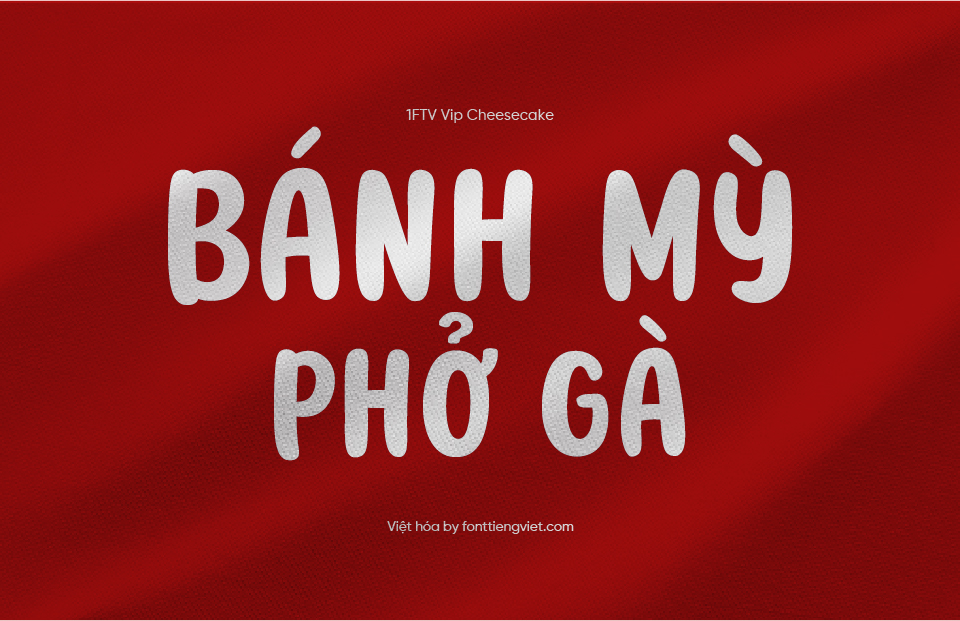
Font Việt hóa 1FTV Vip Cheesecake
Giới thiệu về Font Việt hóa 1FTV Vip Cheesecake
Trong thế giới thiết kế đồ họa hiện nay, việc tìm kiếm một mẫu Font Miễn Phí độc đáo và ấn tượng luôn là ưu tiên hàng đầu của các bạn học sinh và thầy cô giáo. Font Việt hóa 1FTV Vip Cheesecake nổi bật như một lựa chọn hoàn hảo cho các dự án sáng tạo nhờ phong cách ngọt ngào, mềm mại giống như tên gọi của một món tráng miệng hấp dẫn. Đây là bộ phông chữ được tinh chỉnh kỹ lưỡng về dấu tiếng Việt, giúp người dùng dễ dàng trình bày nội dung mà không lo lỗi hiển thị hay mất thẩm mỹ.
Đặc điểm nổi bật của bộ font chữ này
Phong cách thiết kế sáng tạo
Font Việt hóa 1FTV Vip Cheesecake mang trong mình nét vẽ phóng khoáng nhưng không kém phần chỉn chu. Các đường cong của chữ được bo tròn tạo cảm giác thân thiện, gần gũi và đầy năng lượng. Điều này giúp bộ font trở nên cực kỳ phù hợp cho các bài thuyết trình, thiết kế thiệp chúc mừng, bìa sách giáo khoa hay các ấn phẩm trang trí lớp học sinh động.
Tính ứng dụng cao trong học tập
Không chỉ dùng cho mục đích giải trí, bộ font này còn hỗ trợ đắc lực trong việc làm nổi bật các tiêu đề quan trọng. Nhờ khả năng hiển thị rõ ràng trên cả màn hình máy tính và bản in, 1FTV Vip Cheesecake giúp các em học sinh tự tin hơn khi trình bày ý tưởng cá nhân một cách chuyên nghiệp và có gu thẩm mỹ riêng.
Kết luận và hướng dẫn sử dụng